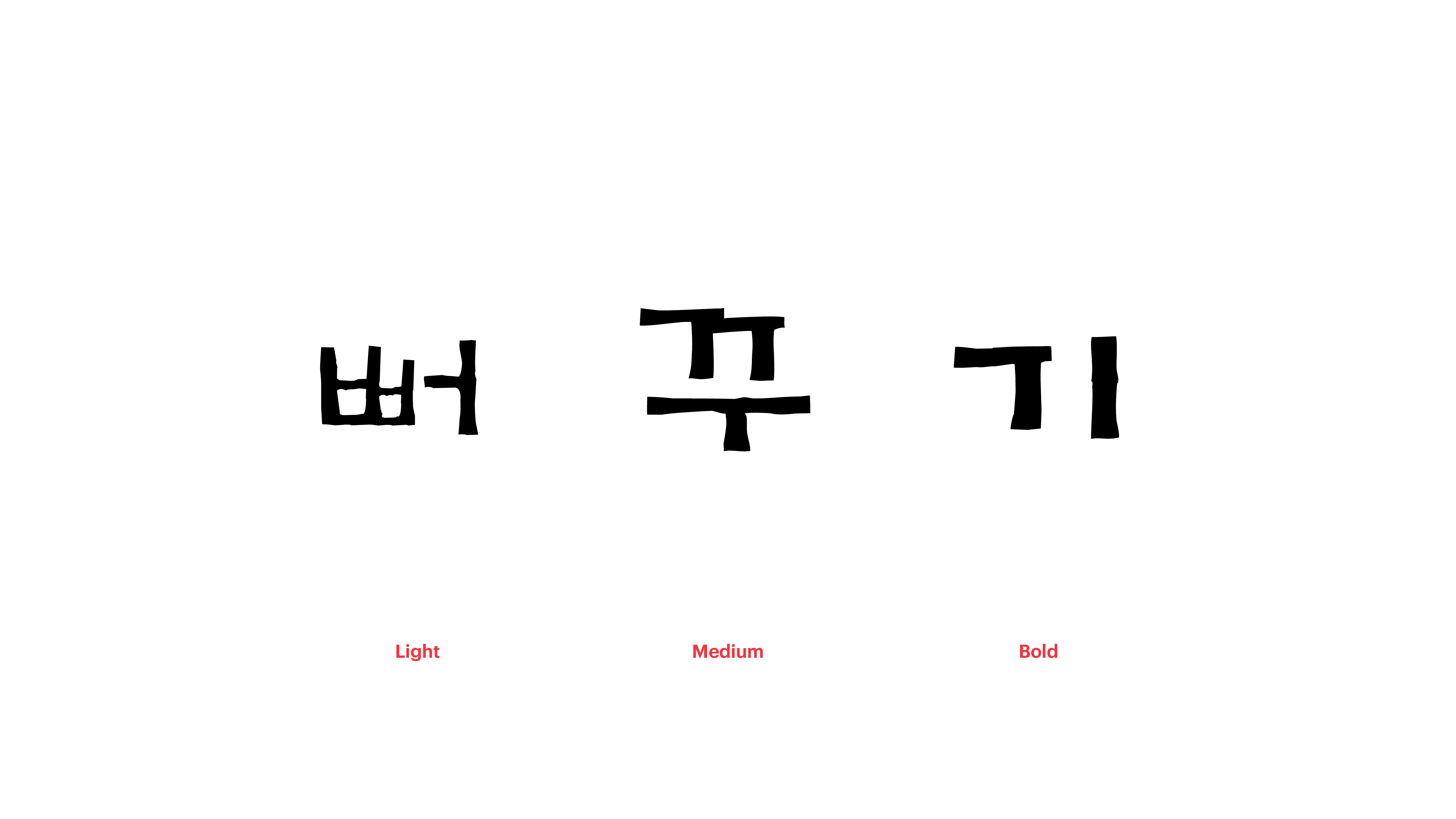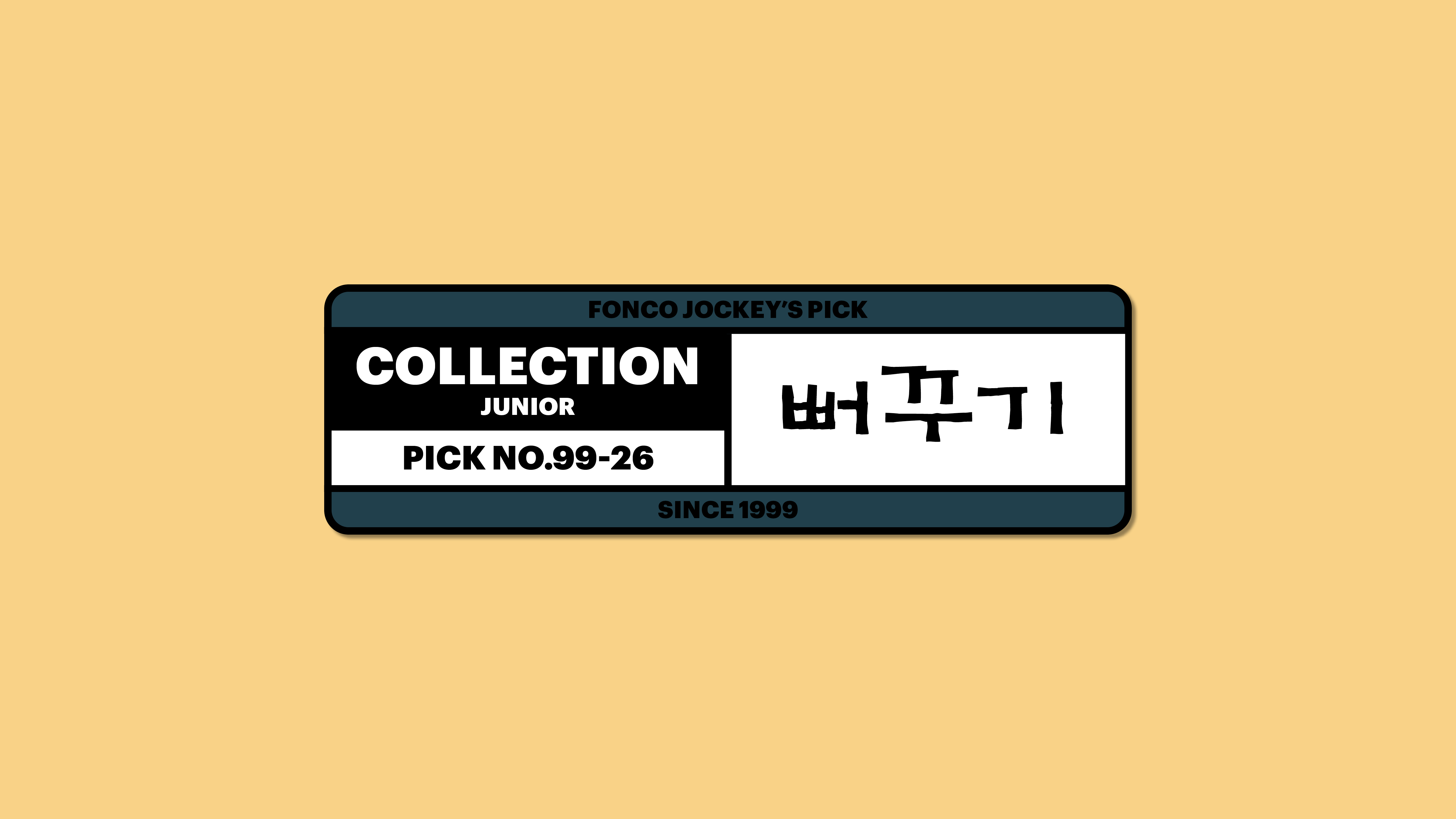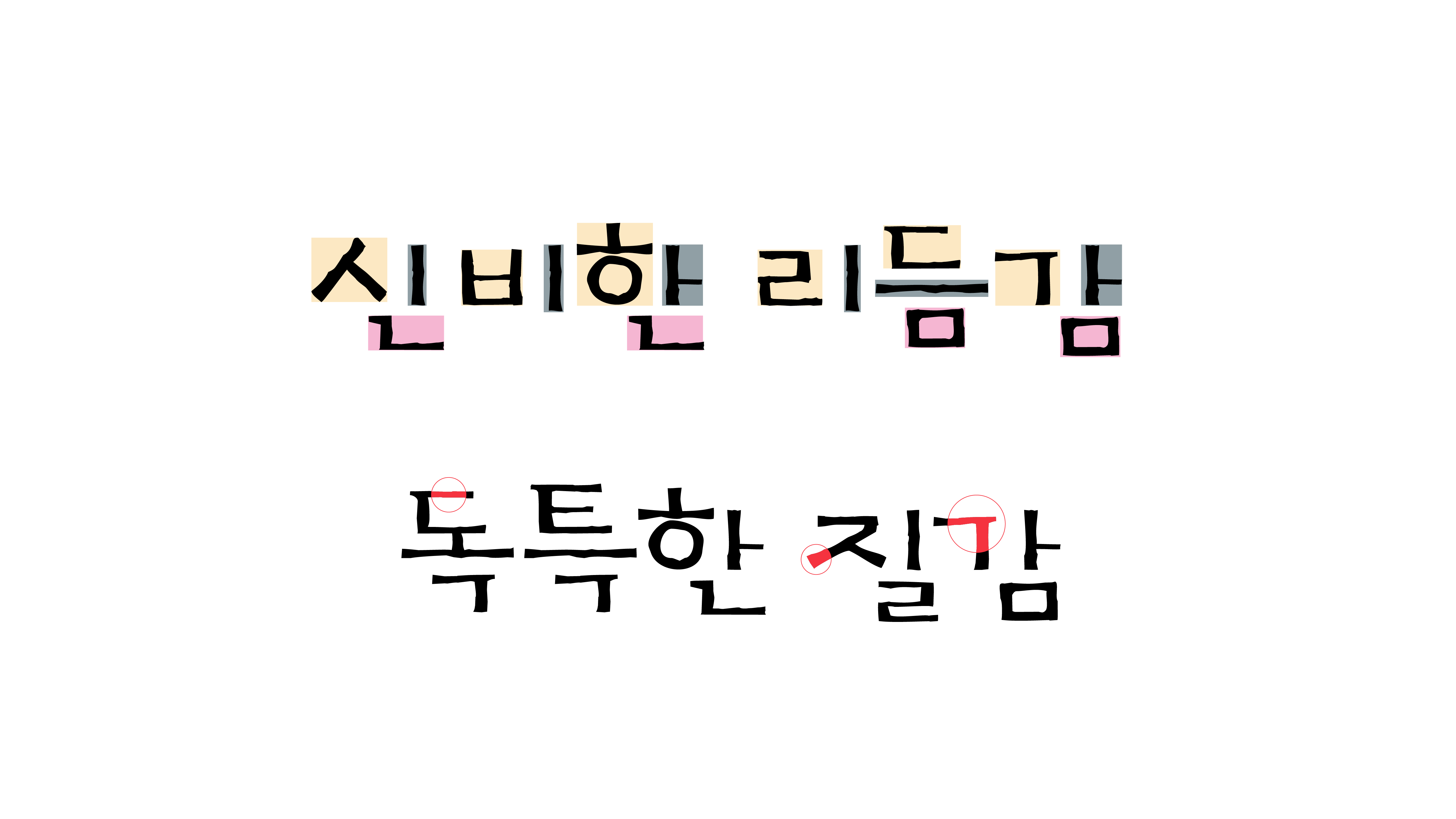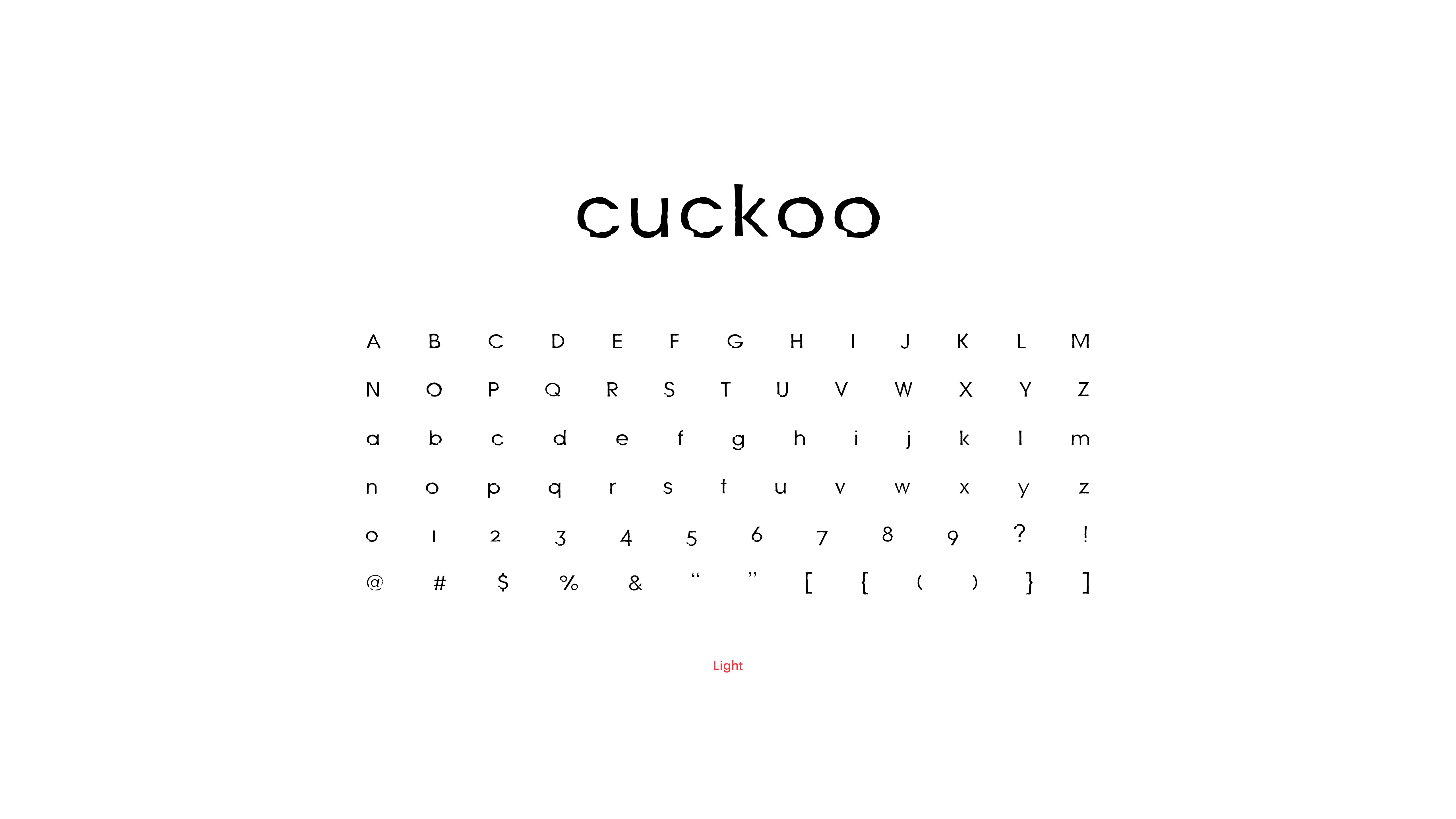
뻐꾸기
Yoon 뻐꾸기
전체적인 균형감보다는 뻐꾸기 울음소리에서 느껴지는 신비한 리듬감에 주목하여 제작한 폰트입니다. 어릴 적 집에 있던 뻐꾸기시계의 복고적 감성을 그대로 살려, 독특한 질감을 덧대었어요. 날아갈 듯, 날아갈 듯, 절대 날아가지 않는, 소중한 추억을 기록할 때 사용해보세요.